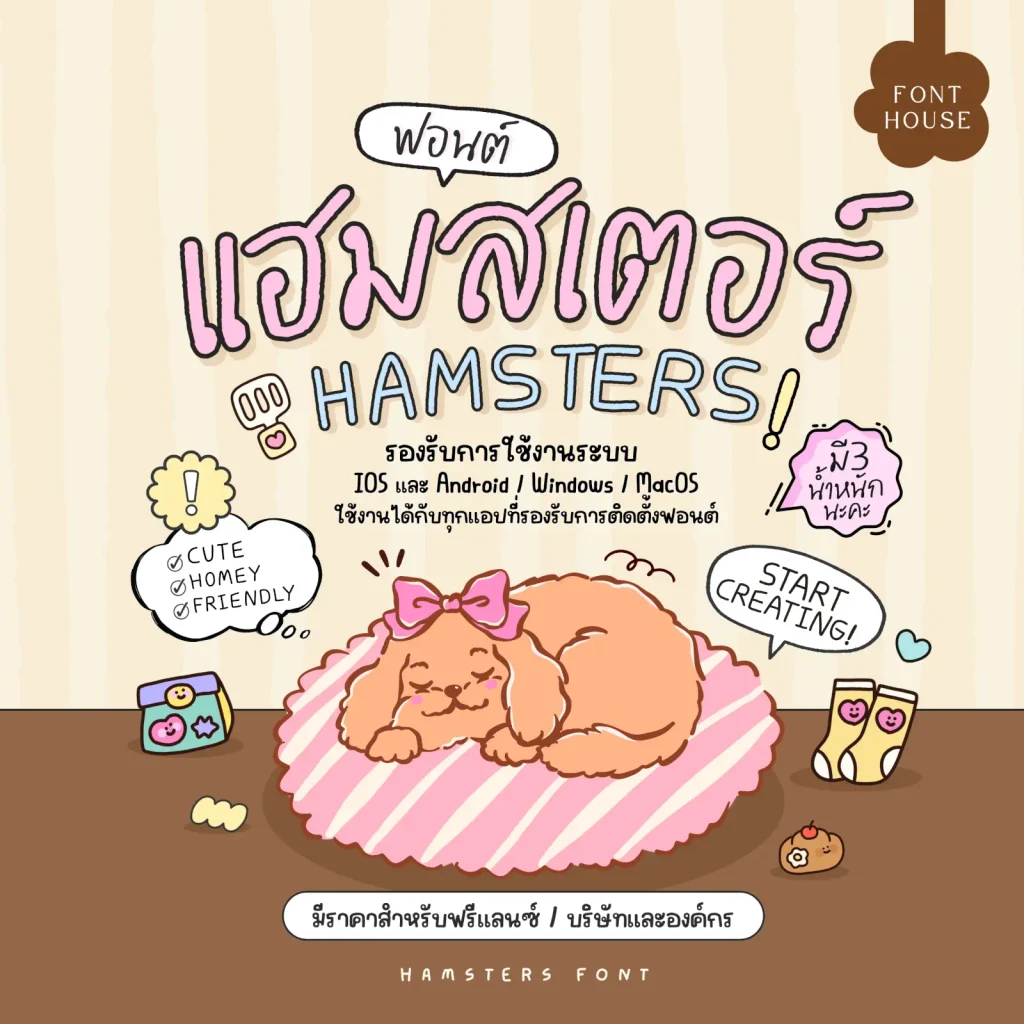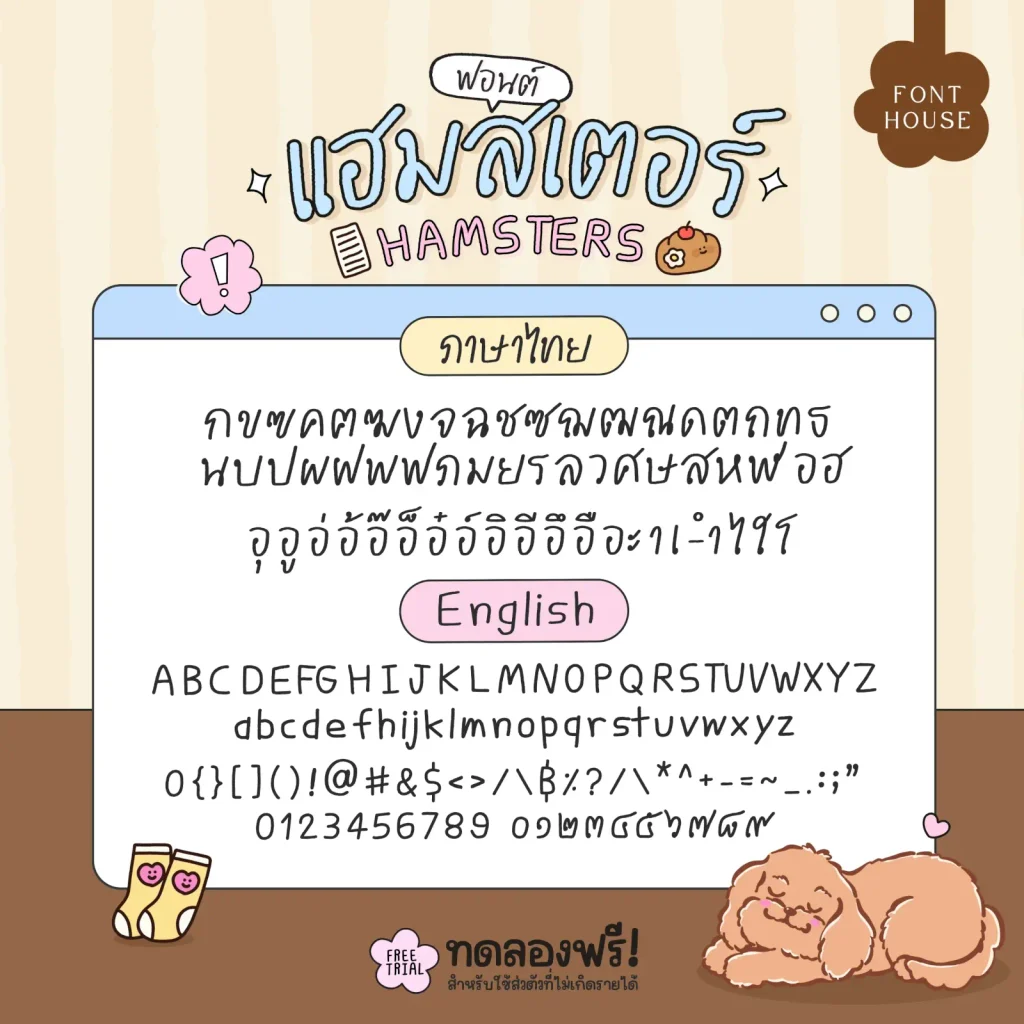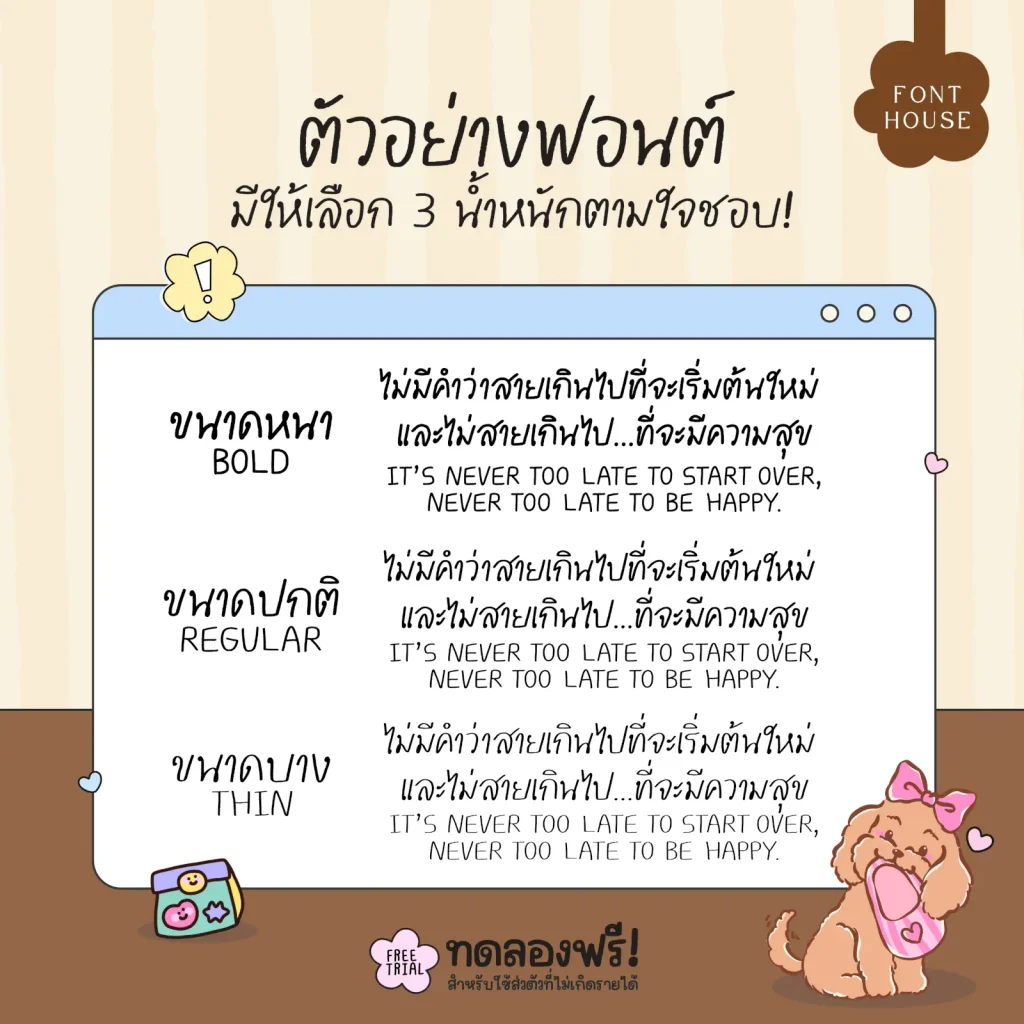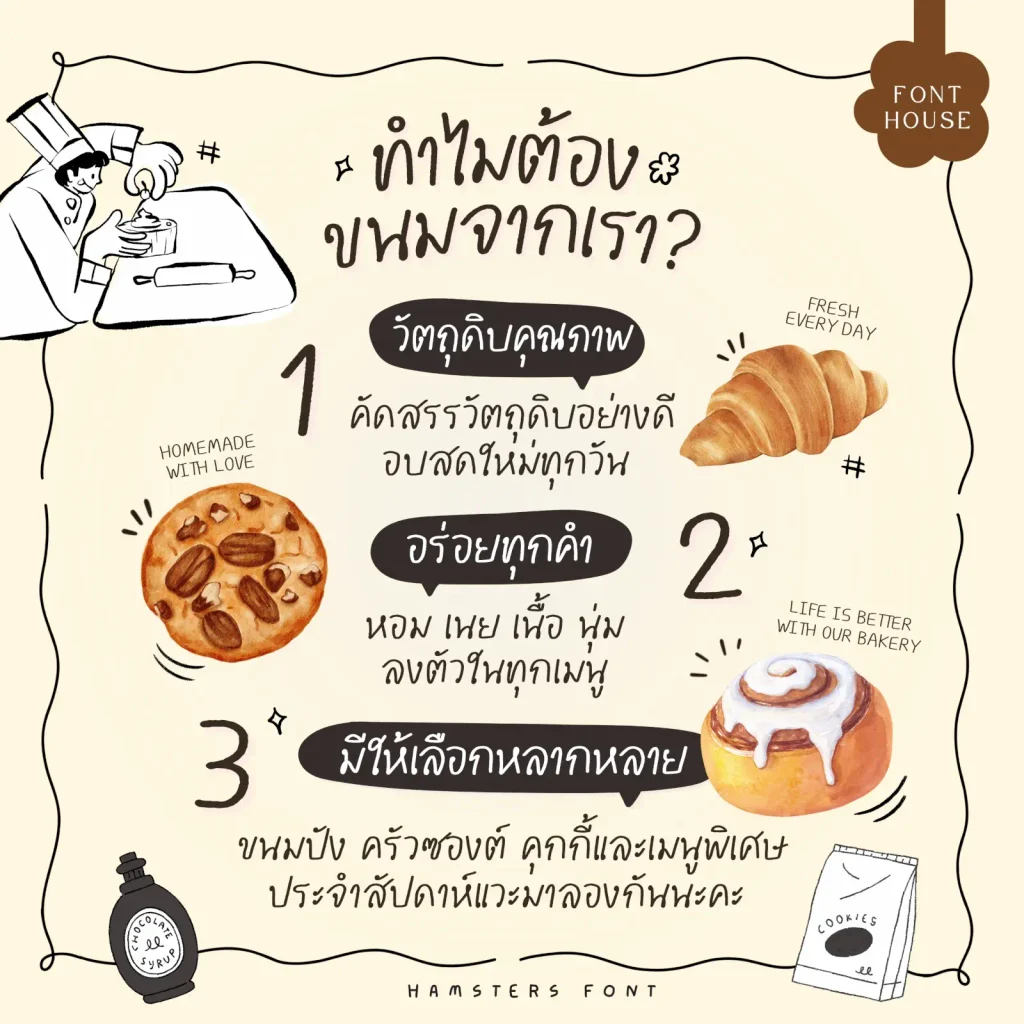
ฟอนต์ แฮมสเตอร์ (FH Hamsters) – ลายเส้นจากแรงบันดาลใจในการเขียนด้วยดินสอ ให้ความรู้สึกเหมือนลายมือที่เขียนขึ้นด้วยมือจริง น่ารัก ซุกซน อบอุ่น และเป็นกันเอง เติมเสน่ห์แบบงานแฮนด์เมด ผ่านลายเส้นเก๋ๆ เหมือนหน้าสมุดวาดเล่นที่เต็มไปด้วยไอเดียและเรื่องราว
- มี 3 น้ำหนัก
แฮมสเตอร์ (FH Hamsters)